შესაძლოა, ბოლო პერიოდში შეამჩნიეთ, რომ ისე სწრაფად ვეღარ კითხულობთ, როგორც ადრე. ამის მიზეზი შეიძლება მხედველობის დაქვეითება ან კოგნიტიური ცვლილებები იყოს… თუმცა კიდევ ერთ საინტერესო და, შეიძლება ითქვას, უჩვეულო საკითხს ე. წ. „ასაკობრივი შრიფტები“ წარმოადგენს.
ახლად ჩატარებულმა კვლევამ აჩვენა, რომ შრიფტებს დიდი გავლენა აქვს ადამიანის კითხვის ტემპზე. ეს გავლენა კი კიდევ უფრო იზრდება, თუ 35 წელზე მეტის ხართ. შონ უოლასის, ბრაუნის უნივერსიტეტის კომპიუტერული მეცნიერების დოქტორანტის თქმით, კითხვის ეფექტურობის გაუმჯობესება შრიფტის მანიპულირებით შეიძლება.
უოლასის გუნდმა 18-დან 71 წლამდე ასაკის 352 ცდისპირი შეკრიბა. მათ ერთი ტექსტის 16 სხვადასხვა შრიფტით წაკითხვა დაევალათ: Avenir Next, Arial, Avant Garde, Calibri, Franklin Gothic, EB Garamond, Helvetica Neue, Lato, Montserrat, Noto Sans, Open Sans, Oswald, Poynter Gothic Text, Roboto, Times და Utopia.
მთელი ამ ჩამონათვალიდან არ არსებობს ერთი უნივერსალური შრიფტი, რომლის შემთხვევაშიც ყველა ადამიანი უფრო სწრაფად კითხულობს… ზოგიერთის კითხვის ტემპს Arial აჩქარებს, ზოგიერთისას კი — Avant Garde. შესაბამისად, ინდივიდუალური განსხვავებები უფრო მნიშვნელოვანი იყო, ვიდრე ნებისმიერი საერთო ეფექტი. საინტერესოა, რომ ის შრიფტები, რომლებსაც თავად ანიჭებდნენ უპირატესობას, სულაც არ ეხმარებოდათ სწრაფად კითხვაში. მაგალითად, შეიძლება, Helvetica-ს ვიზუალი მოგწონდეთ, მაგრამ Open Sans-ით უფრო სწრაფად კითხულობდეთ.
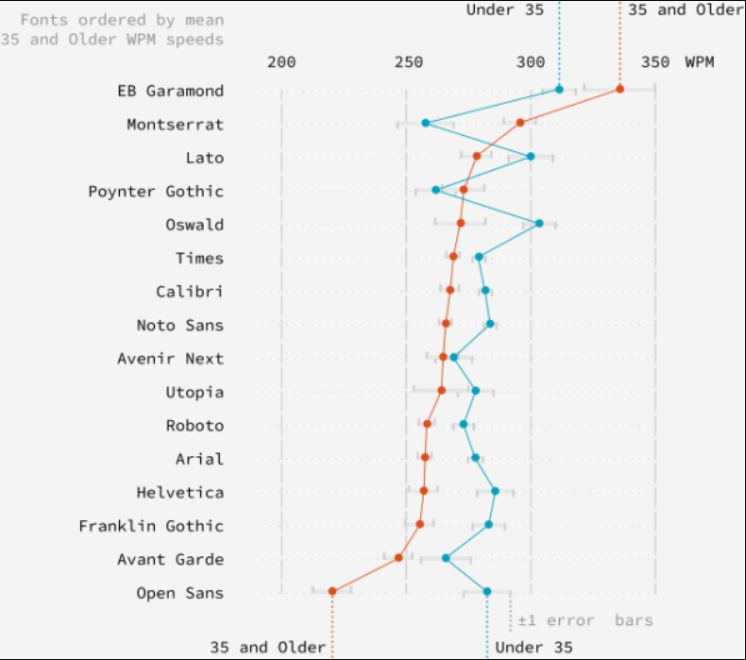
ამასთან, ერთი დასკვნა ნათელი იყო: 35 წელზე დიდი ასაკის მონაწილეები ყველა შრიფტით, საშუალოდ, უფრო ნელა კითხულობდნენ ახალგაზრდა მონაწილეებთან შედარებით. გამონაკლისს მხოლოდ EB Garamond და Montserrat წარმოადგენდა. ამის მიზეზად კი ის დასახელდა, რომ Monsterrat-ში ყველაზე მაღალი x-ია გამოყენებული. წარსულში კი ტიპოგრაფები შრიფტებში მაღალი ზომის x-ს იყენებდნენ, რათა წაკითხვა უფრო ადვილი ყოფილიყო.
რაც შეეხება EB Garamond-ს, მას ისეთი სერიფები აქვს, რომლებიც კლასიკურს იერს უზრუნველყოფს. ეს კი ხანდაზმულ მკითხველს ტექსტის უკეთ აღქმაში ეხმარება.
რეალურად, კვლევის შედეგები დიზაინის დიდ პრობლემას განაზოგადებს — საშუალო მომხმარებელი არ არსებობს, ვერ შეიქმნება უნივერსალური, ყველაზე მორგებული პროდუქტი.